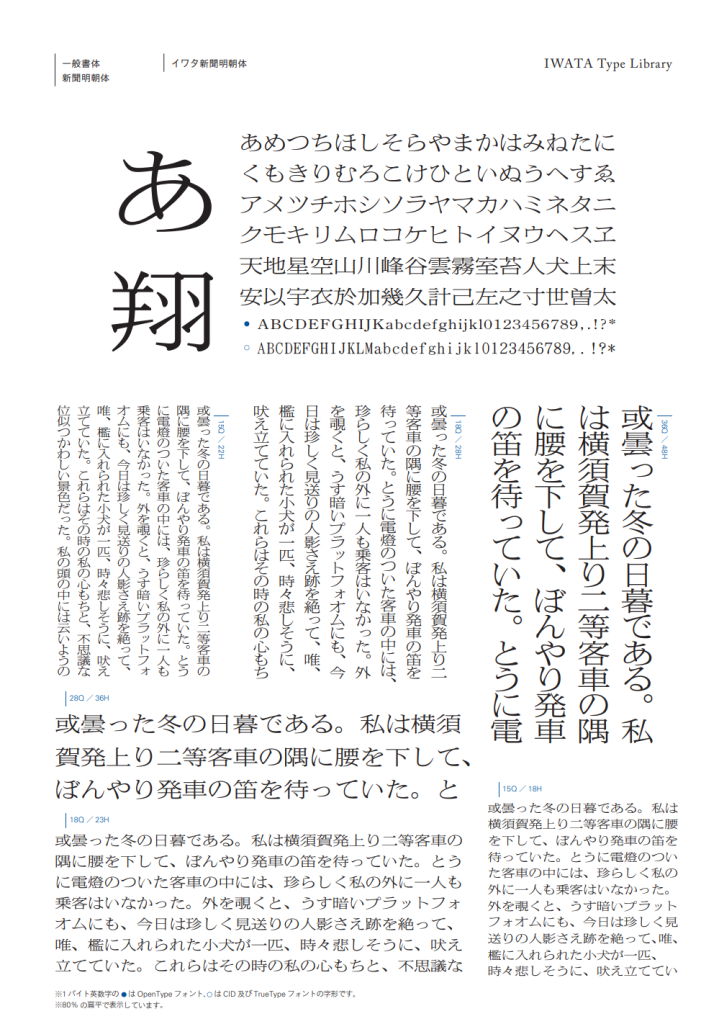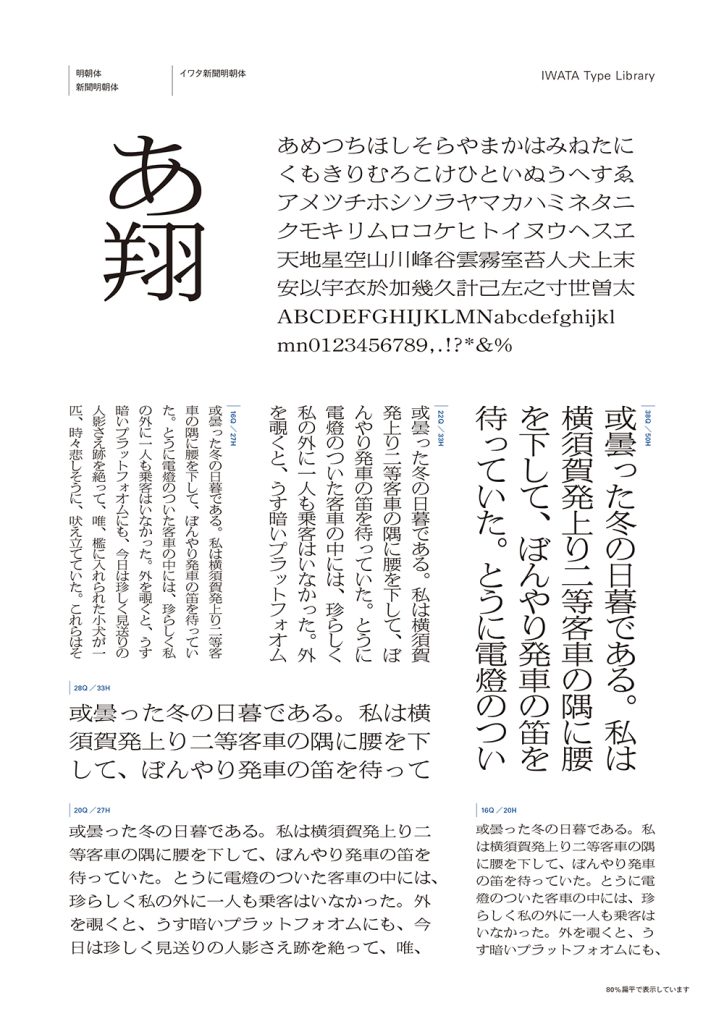
昭和16 年に岩田母型製造所が開発した新聞本文用書体「岩田新聞明朝体」を源流とし、活字由来の字形を再現した歴史ある新聞明朝体で、多くの新聞社に採用されてきました。いわゆる新聞書体の特徴を色濃く残した佇まいが魅力で、広告や装丁などにも幅広く活用されています。80% 扁平に変形使用することを想定して設計されています。
書体デザインのポイント
たっぷりしたふところの安定感とシャープさの組み合わせに加え、仮名の美しく伸びやかなエレメントが特徴的です。(扁平率:80%)